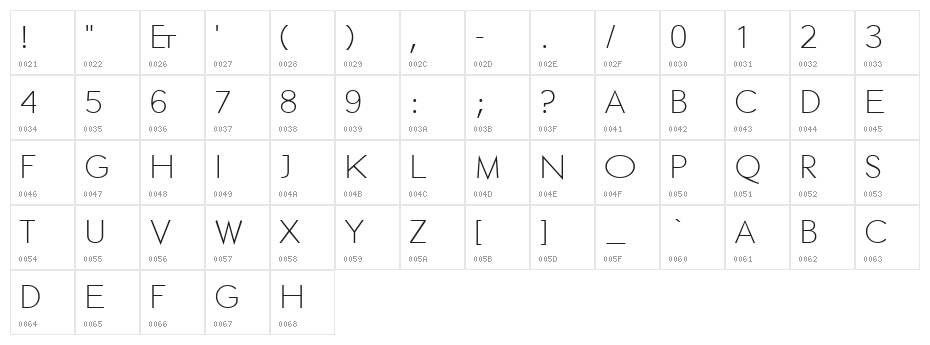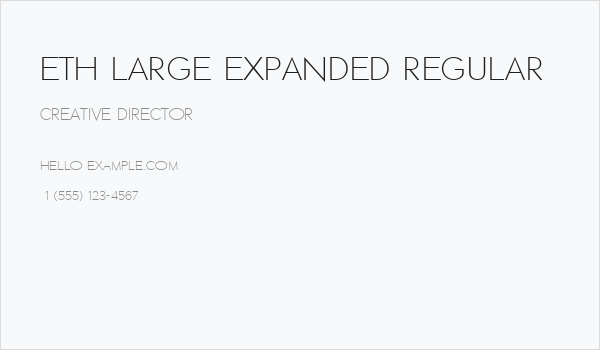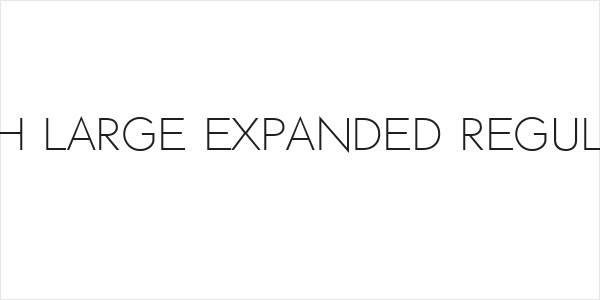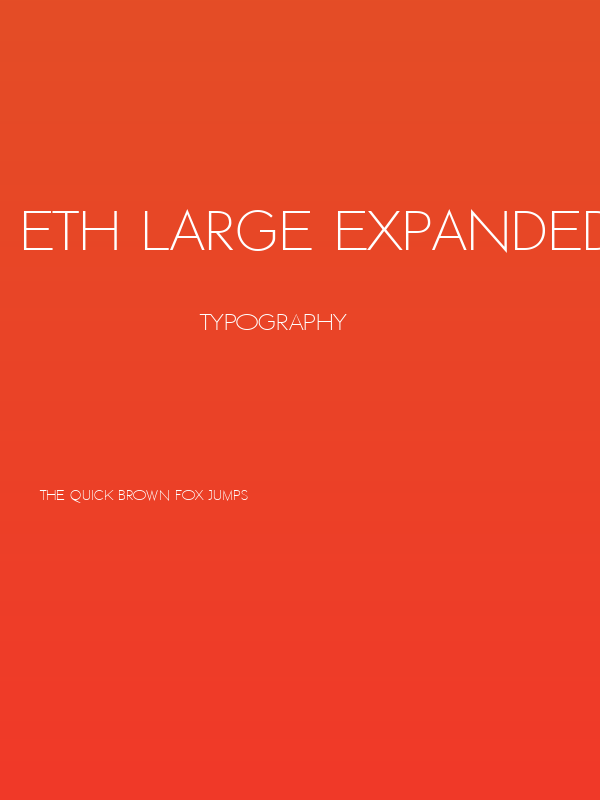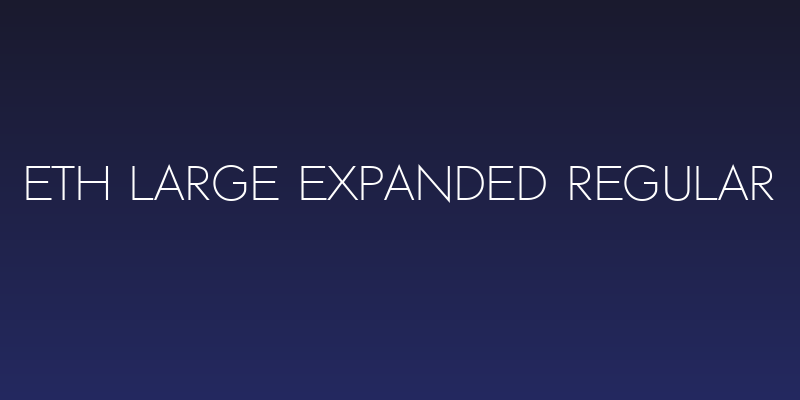
ETH Large Expanded Regular Font
✎ Sans Serif
| 分类 | Sans Serif |
| 宽度 | Expanded |
| 使用场景 | Headlines, Body text, Logos |
| 推荐项目 | Ideal for branding, advertising, web design, and editorial projects where clarity and modernity are essential. |